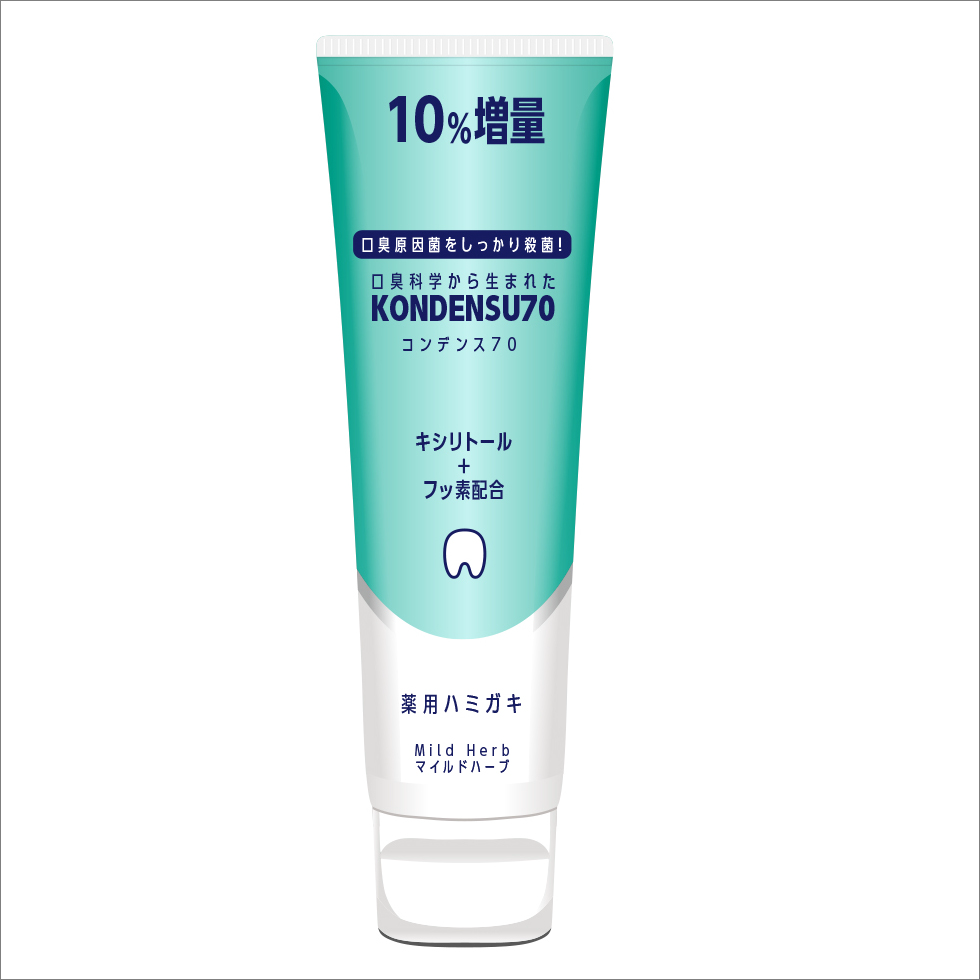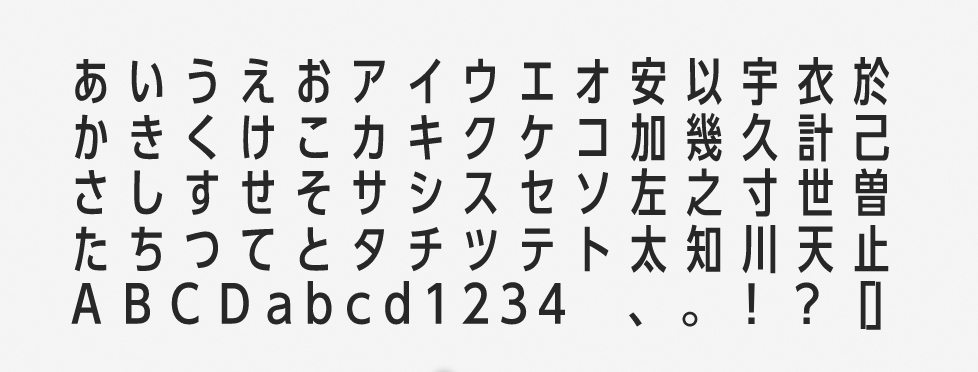
「UD新ゴ コンデンス70」について
「文字のかたちが分かりやすいこと」「文章を読みやすいこと」「読み間違えにくいこと」という3つのコンセプトに沿って開発されたモリサワUDフォントの1つです。UD新ゴをベースにしながら字幅を狭めたコンデンス書体(長体)で、限られたスペースに多くの情報を掲載しやすくなります。
「UD新ゴ コンデンス70」の特徴
膨大な情報の掲載が必須とされる食品の成分表示やパッケージの注意書きなどでは特に便利です。読み間違えやすいフォントでは大きなトラブルにつながりますが、ユニバーサルデザインに配慮されたフォントであれば誤読は多発しません。
フォント名の「70」は長体率を示し、このほかにもUD新ゴ コンデンスには90%から50%までの5段階があります。文字の変形で生じる画線の歪みが解消され、最適なバランスで整えられているため、長体でも読みやすいフォントです。
作例はチューブ型のパッケージで、情報を掲載するスペースが極端に限られます。UD新ゴ コンデンス70を使うことにより、横組みで文字を並べることができているデザインです。各種の注意書きなどに使っても、文字を見やすいフォントと言えるでしょう。